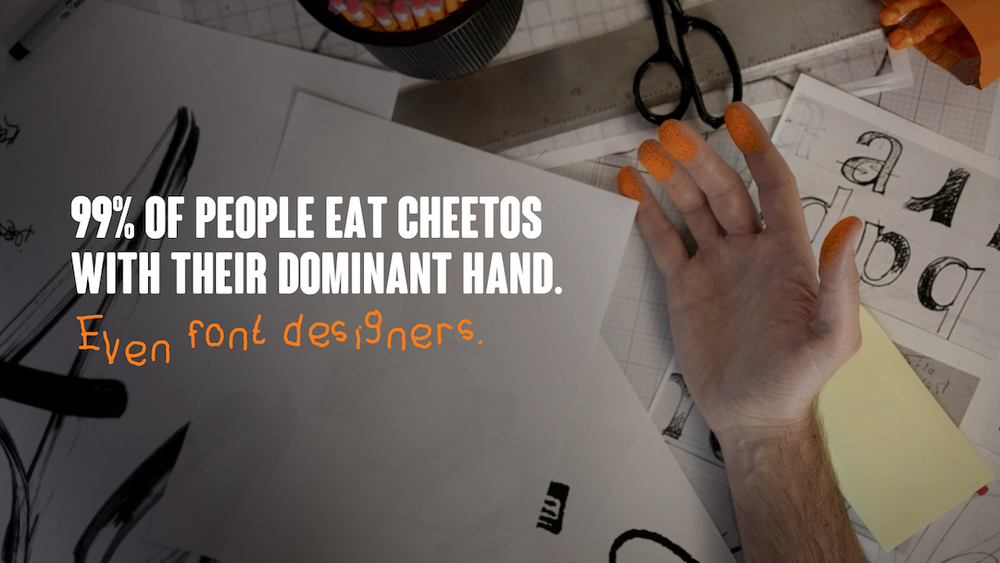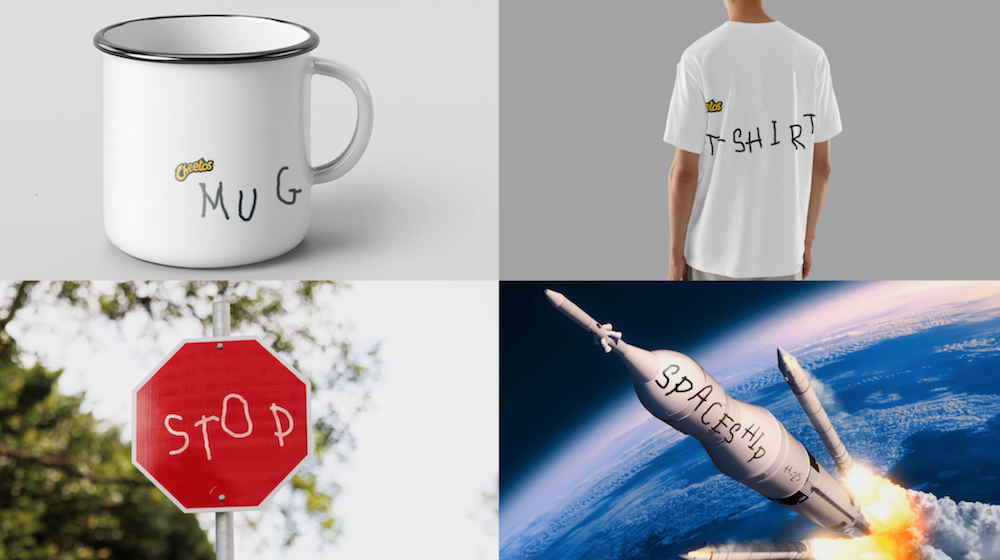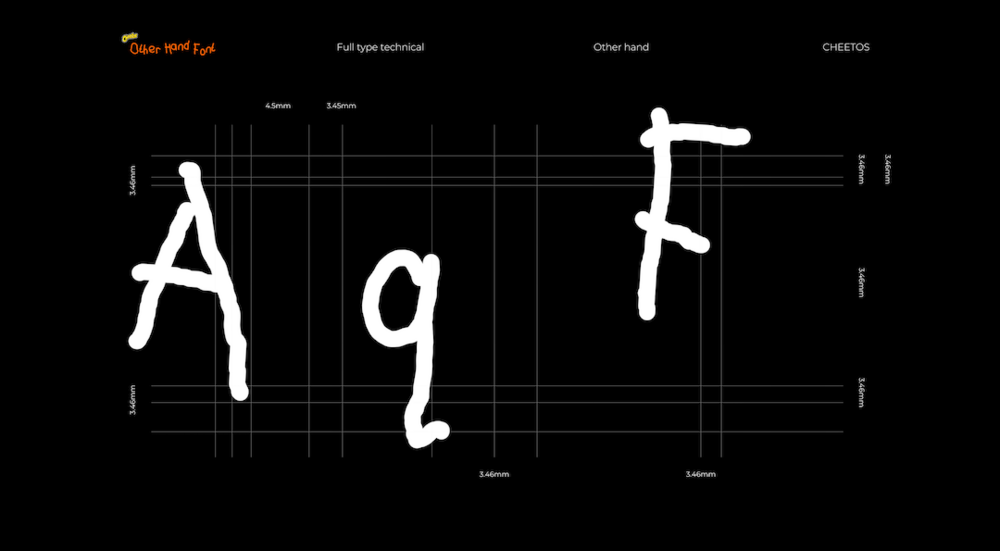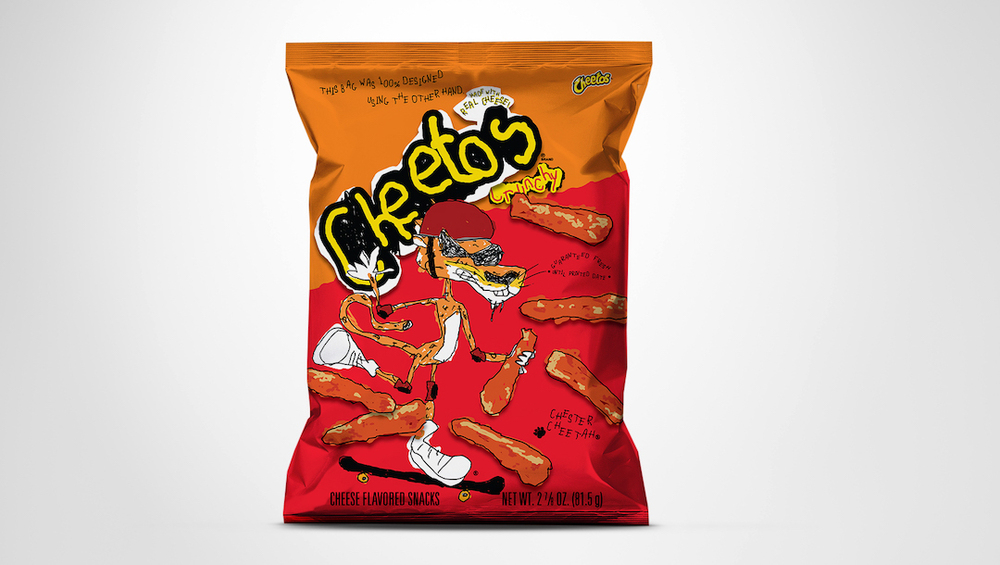
Cheetos, 23 Ocak Dünya El Yazısı Günü’nü, cips yedikten sonra oluşan yapışkan, parlak turuncu parmak uçlarından ilham alarak tasarlanan “The Other Hand Font” ile kutladı. Goodby Silverstein & Partners ekibi tarafından oluşturulan yazı tipi, tamamen baskın olmayan eller kullanılarak tasarlanmış.
“The Other Hand Font”, Cheetos severlerin hayatta tek eli sürekli turuncu tozla kaplı olarak yaptığı şeyleri konu alan “The Other Hand” kampanyasının en yeni üyesi. “The Other Hand” kampanyası, insanların %99’unun baskın elleriyle cips yediği gerçeğinden hareketle yaratıldı. Bu durum insanları, cips yedikleri sırada yaptıkları şeyleri baskın olmayan elleriyle yapmaya itiyor. Kampanya, milyonlarca insanda bulunan bu evrensel eğilimi, mizahla karışık bir şekilde onurlandırıyor. Mizahın üretildiği kaynak da tabii ki baskın olmayan elle yapılan kötü, hatalı ve absürt işler. Kampanyayla ilgili haberimizi aşağıda görebilirsiniz.